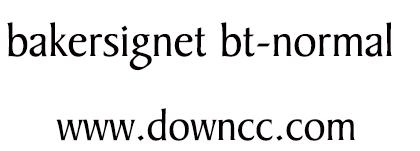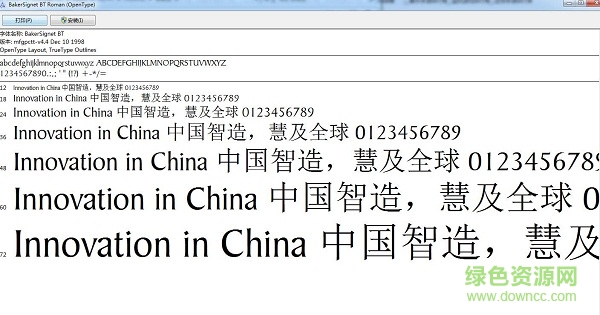
bakersignetbt roman字體是一款普通常規(guī)襯線字體,字面結(jié)構(gòu)舒展大氣,閱讀效果好,可以通用于廣告宣傳、平面設(shè)計、書籍排版等各大領(lǐng)域,歡迎大家免費下載!
結(jié)構(gòu)嚴(yán)謹(jǐn),整齊均勻,有極強(qiáng)的筆畫規(guī)律性,從而使人在閱讀時有一種舒適醒目的感覺。在現(xiàn)代印刷中主要用于書刊或報紙的正文部分。